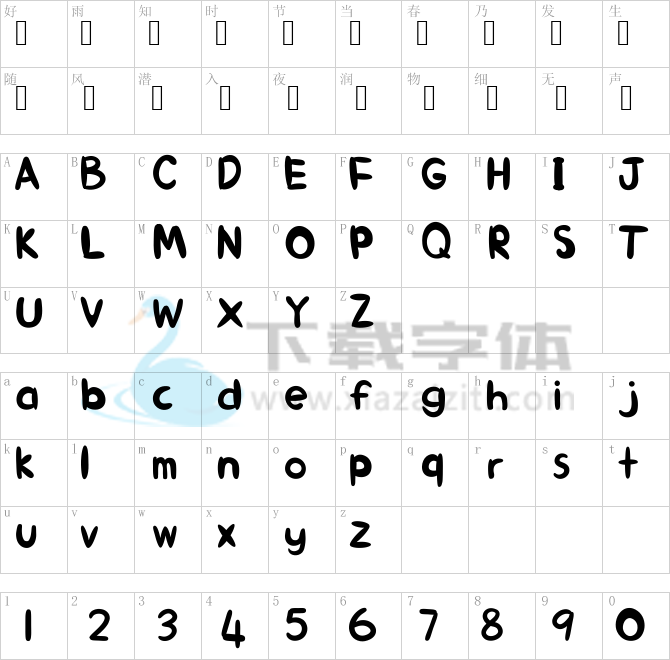
ALIN_KID.ttf字体下载,这款字体结构工整、笔画清晰,兼顾美观与易读性,适用于标题、正文、海报、包装、LOGO 等多种场景。字形优雅稳定,风格百搭耐看,适配日常排版与创意设计,让文字呈现更舒适、更具质感。ALIN_KID.ttf字体下载一笔一画,皆是细节,以均衡的比例、流畅的线条打造舒适视觉体验,字形端正大气,风格简约现代。无论是商业设计、品牌宣传还是日常排版,都能轻松驾驭,让文字更有格调与力量。ALIN_KID.ttf字体下载字体下载。